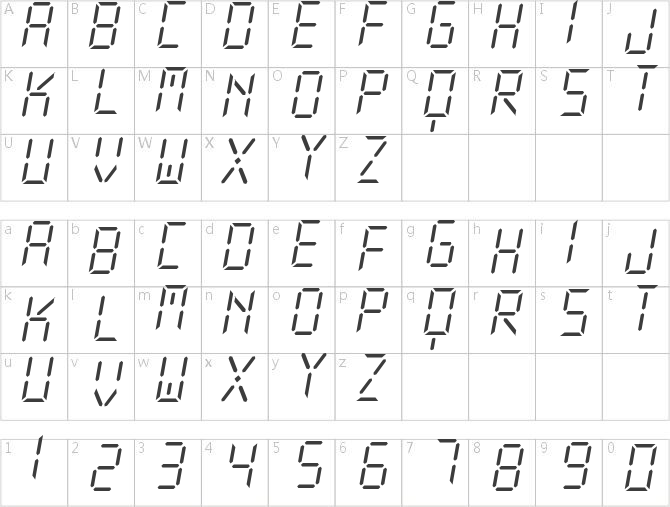
New-X-Digital-tfb-Light
New-X-Digital-tfb-Light介紹
New-X-Digital-tfb-Light字體字庫是一款讓人賞心悅目、百看不厭的英文字體,適合各類廣告和產品包裝設計應用,字體大小0.04MB,格式為ttf字體,上傳用戶是曾紹文,作者/版權方為未知